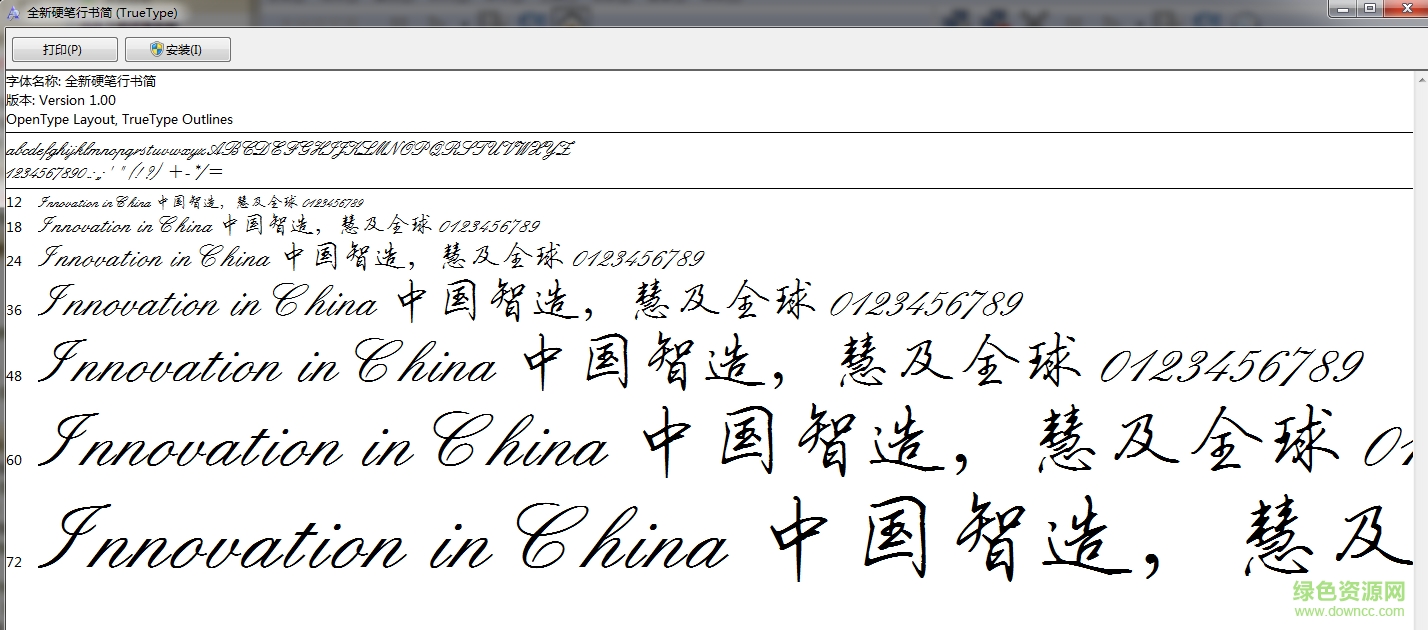
qxyingbixing
qxyingbixing是什么字體?qxyingbixing字體就是全新硬筆行書簡(jiǎn)體,這款行書字體的結(jié)構(gòu)布局非常端正平穩(wěn),用筆不急不緩,韻意深長(zhǎng),大氣雅致,需要就來(lái)綠色資源網(wǎng)下載吧!
行書字體基礎(chǔ)
【上下貫穿】
貫穿行氣是行書布局謀篇的最重要的技巧。
qxyingbixing
【調(diào)整輕重】
“險(xiǎn)中求平”是造型藝術(shù)美的一個(gè)重要因素,而要取得平衡,必須學(xué)會(huì)調(diào)整輕重。
【力求和諧】
和諧主要包括一下幾點(diǎn):筆觸和諧統(tǒng)一、間白和諧統(tǒng)一、風(fēng)格和諧統(tǒng)一、字體和諧統(tǒng)一。